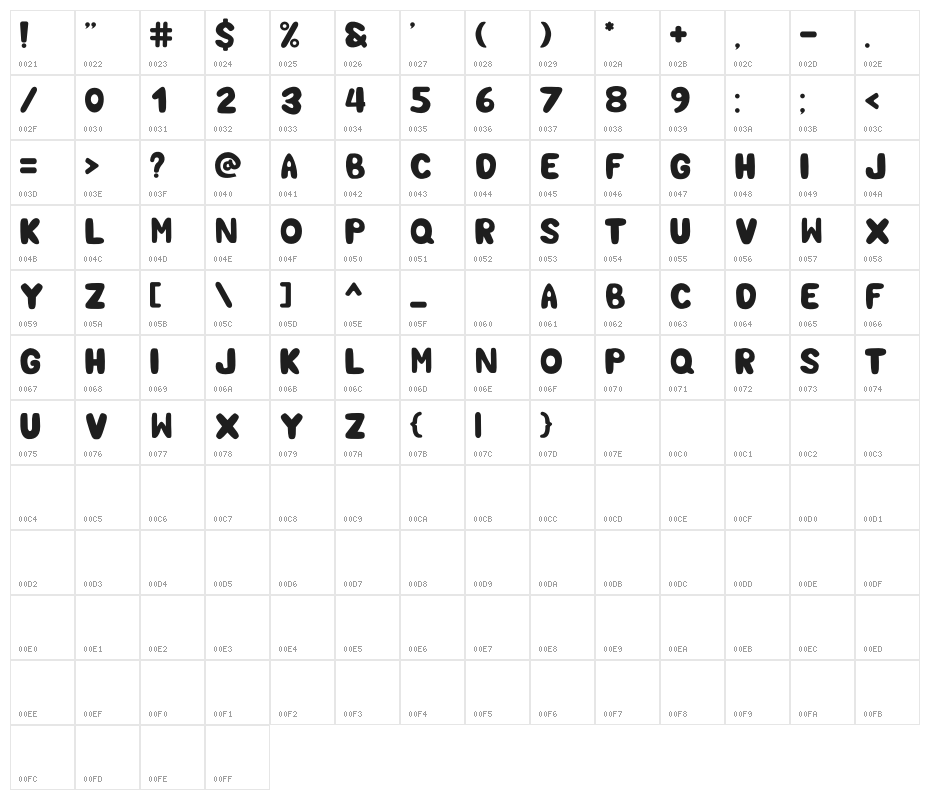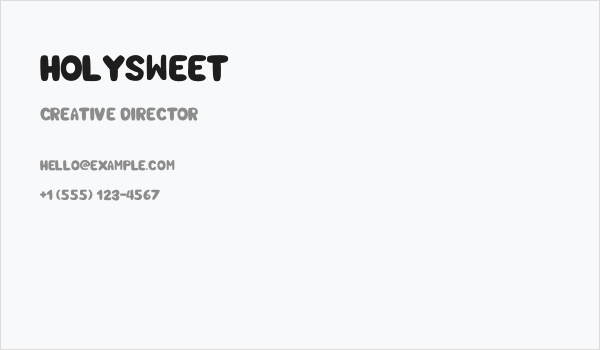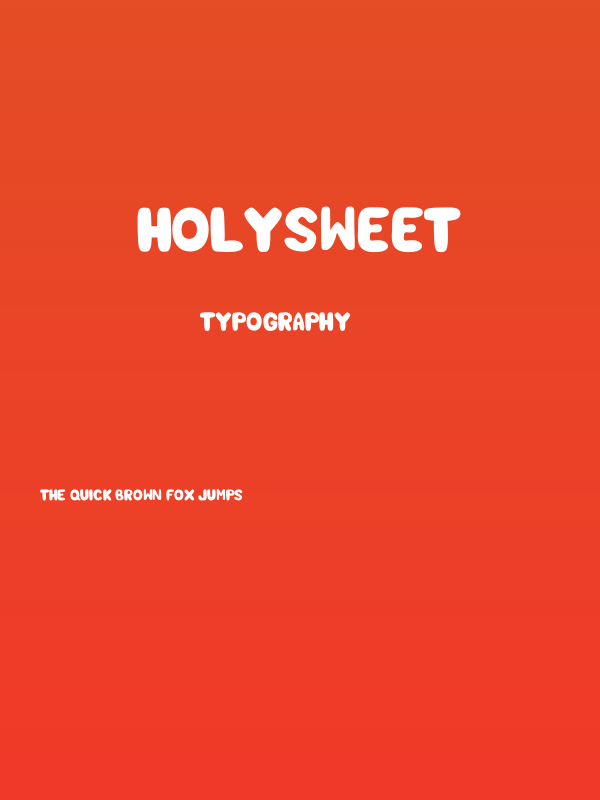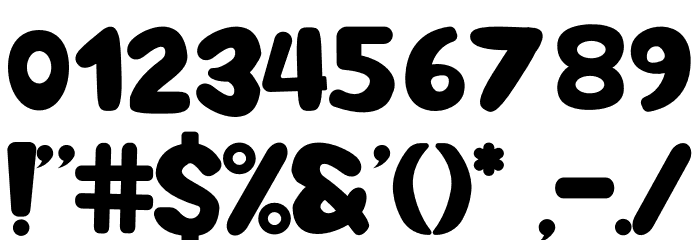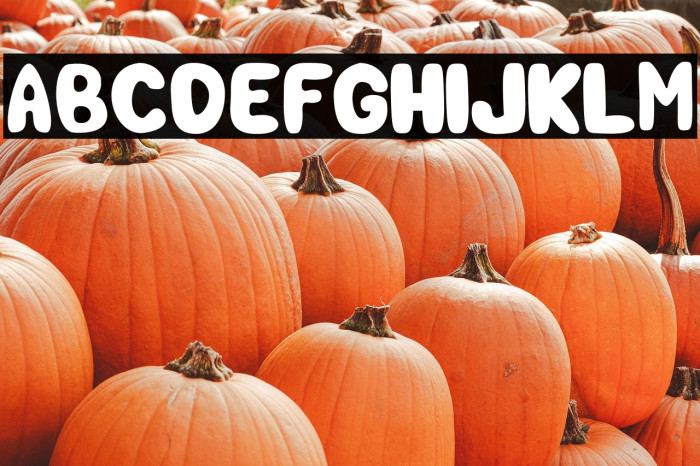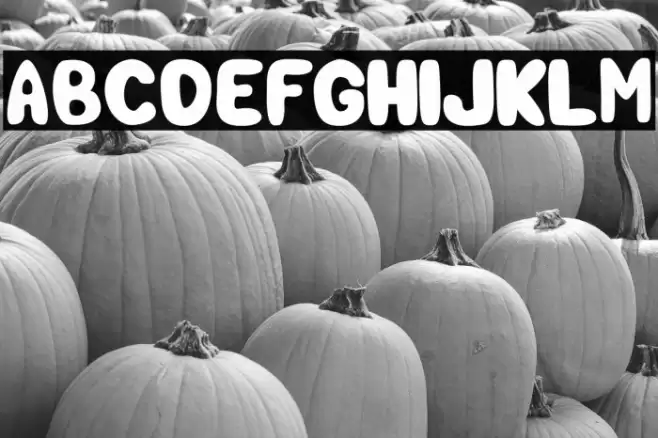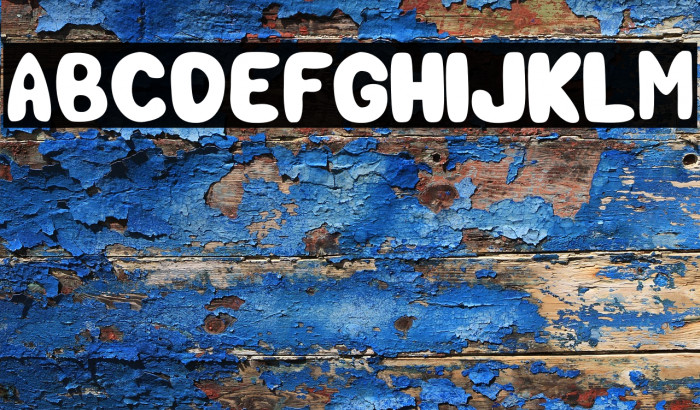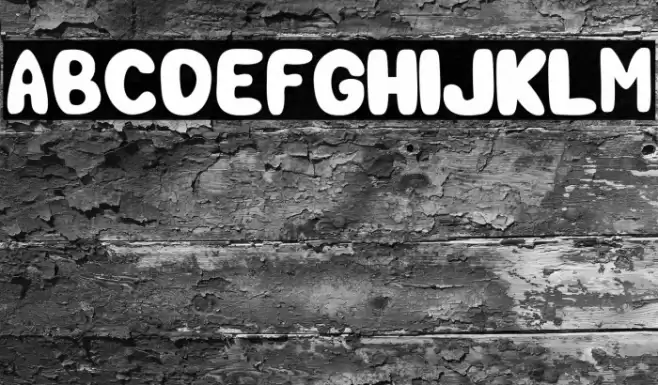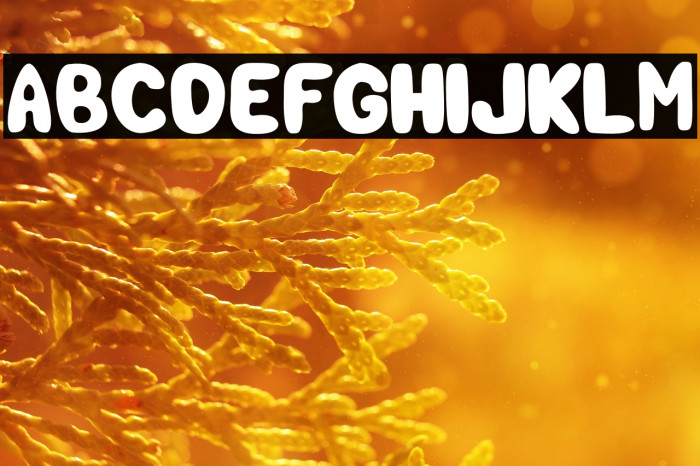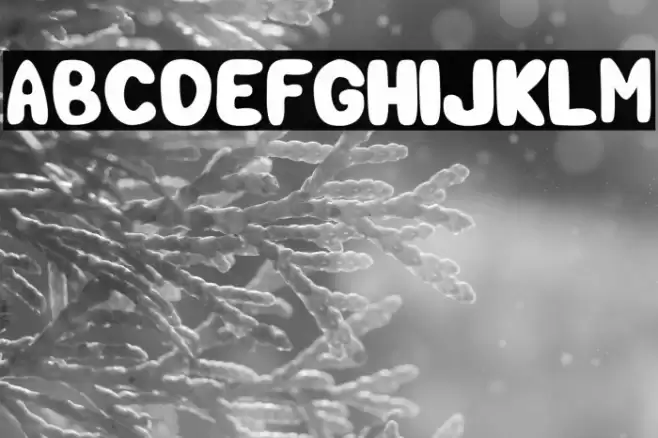
HOLYSWEET Font
| Estilo general | Playful, Retro |
| Proyectos propuestos | Perfect for children's books, playful branding, party invitations, or any project needing a whimsical touch. |